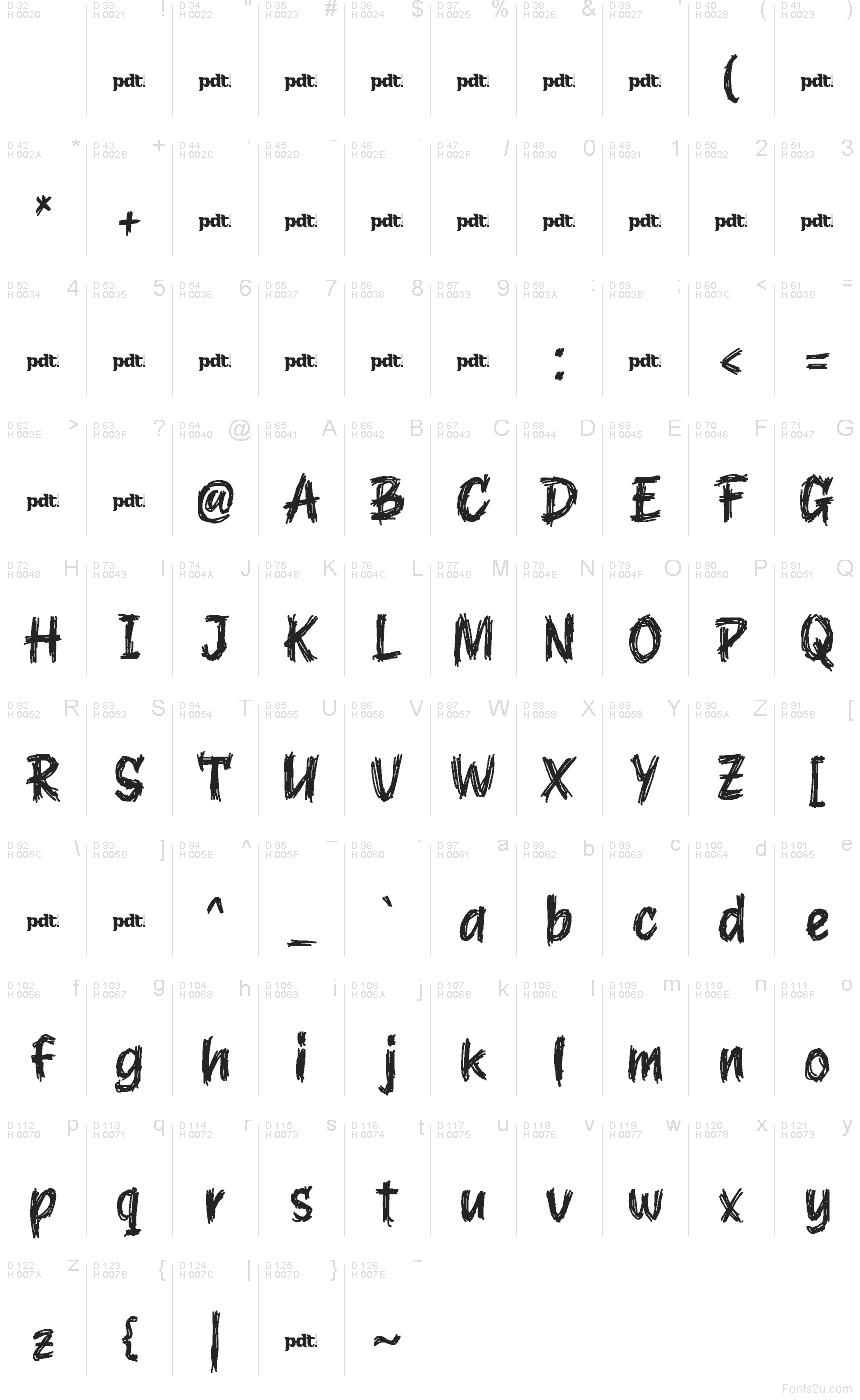
ALGEON od Productype je bezplatné „trash“ písmo s drsným, poškrábaným vzhledem, které čerpá energii přímo z punkových zinů. Písmena vypadají jako nasekaná k sobě pomocí opakovaných zubatých tahů, hrubých překryvů a nerovných hran. Celé písmo tak působí hlasitě, neklidně a záměrně nespoutaně.
Hodí se na plakáty, obaly alb, streetwearovou grafiku, hororové titulky a letáky na akce, kde potřebujete, aby bezplatné písmo neslo urgentní, ručně vytvořený náboj bez pocitu úhlednosti. Použijte ho na krátké nadpisy, názvy kapel nebo monogramy, zejména pokud chcete, aby velká písmena vypadala, jako by byla rychle vyškrábnutá fixou nebo žiletkou.